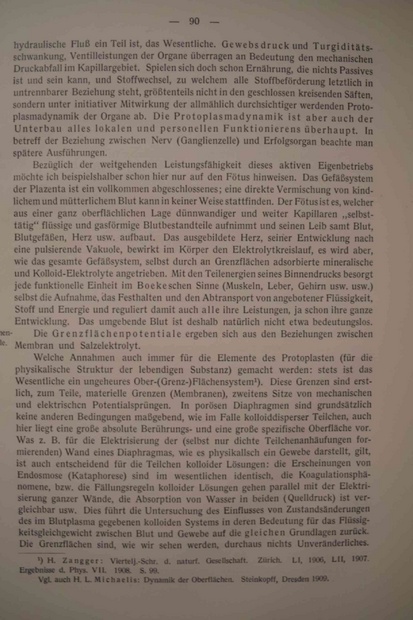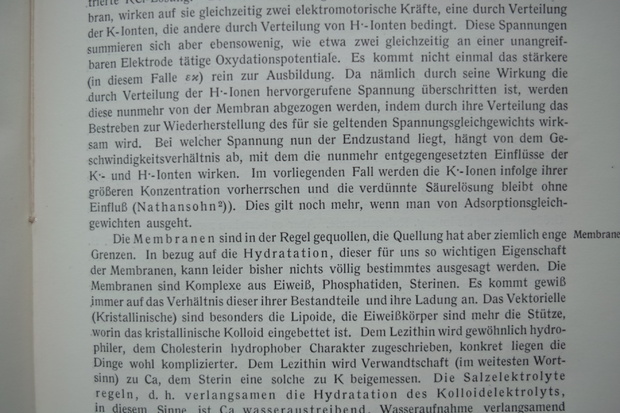
welcher font ist das?
nachdem mich http://www.identifont.com/identify.html auch nicht weitergebracht hat, die frage also an euch.
wer kennt diese schrift?
nachtrag:
vielen dank schonmal für die antwort bertel... hier ein besseres foto
markant an dieser schrift für mich laien sind die großbuchstaben wie M, Q, K..
Das ist schon arg klein … Century Roman könnte passen, die gab es um 1900.
Die Romana ist allerdings für Leseschriftgrößen ziemlich ungeeignet. Weitere Schriften findest Du hier: http://www.typografie.info/2/showthread.php/24484-»Römische-Antiqua«
Danke für die Beiträge. Ich weiß nun wonach ich zu suchen habe... Romanisch, Römisch-Antiqua, Römische-Antiqua, etc...
Wahrscheinlich wird exakt dieser Schnitt nicht digitalisiert vorliegen...
Mich würde dennoch interessieren welche Schriftgießerei exakt diesen Schnitt herstellte..
Besteht ein Zusammenhang zwischen Örtlichkeit des Verlags und benutzter Schriftarten? Daß quasi die Verlage bevorzugt bei Schriftgießereien um die Ecke einkauften???
Beim Georg Thieme Verlag in Leipzig könnte das um 1926 dann welche Schriftgießerei gewesen sein ????????????
Besteht ein Zusammenhang zwischen Örtlichkeit des Verlags und benutzter Schriftarten? Daß quasi die Verlage bevorzugt bei Schriftgießereien um die Ecke einkauften???
Beim Georg Thieme Verlag in Leipzig könnte das um 1926 dann welche Schriftgießerei gewesen sein ????????????
Eine belastbare Aussage wird man aus dieser Vermutung nicht ableiten können, das ist die reine Kaffeesatzleserei. Zumal erstens nicht der Verlag die Schriften kauft, sondern die Druckerei (auch wenn der Verlag bestimmte Schriften verlangen kann) und zweitens nicht einmal klar ist, ob die Schrift überhaupt als Komplettgußschrift bei einer Gießerei gekauft wurde oder z. B. auf der Monotype gegossen, was ja 1926 für ein Fachbuch gut möglich, wenn nicht sogar sehr wahrscheinlich ist.